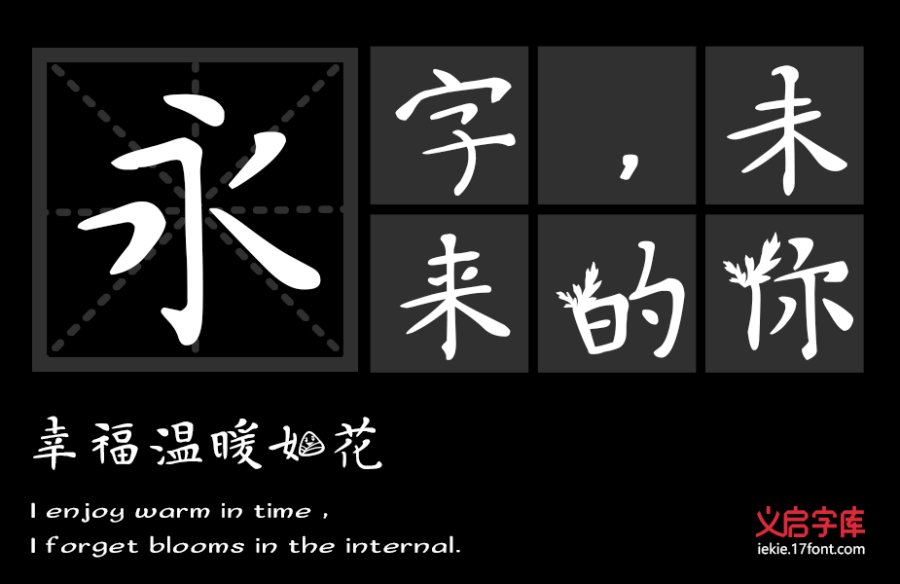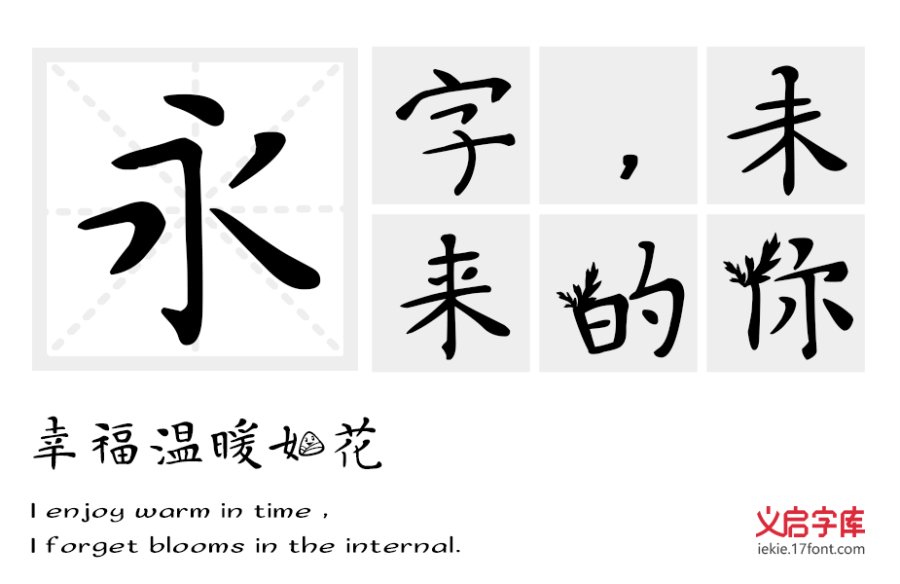
义启端午体,这款字体设计的灵感来源于端午节,是义启字库出品的节日系列字体中的其中一款节日应景字体。
端午节,又称端阳节、龙舟节等,是我国重要的传统节日。
端午节源自天象崇拜,由上古时代龙图腾祭祀演变而来。端午节有丰富的文化内涵,而且活动丰富多采,如:会挂艾叶、饮雄黄酒、赛龙舟、吃粽子等。
记得每年的端午节前后,我妈妈总喜欢在门边挂艾叶,这也加深了我对端午的情感。在义启端午体中,设计师也为字体挂上艾叶。在部分笔画上,以一片艾叶表示。飘扬的艾叶,很有时节的视觉,随风飘扬,满是春的感觉。
端午节少不了粽子,尽管南咸北甜,但人们对粽子的喜爱不减。应节的义启端午体当然少不了粽子元素,设计师在设计字体时不忘民族传统,部分“口”字偏旁的字体,以“粽子”图案代替,该图案还有眼睛笑脸,十分生动有趣,给人一种温暖亲切感。另外,如果大家平时看到一些图片字体但又不知道是什么字体名称时可以通过字体识别功能来进行图片识别字体。
在南方,赛龙舟是少不了的。特别是靠近河海地区。龙作为端午节的图腾,在义启端午体中也有表现。设计师在部分笔画中增加了“龙”的形象,非常威猛且神采奕奕。龙在中国比喻美好的事物,同时也是民族的象征。
义启端午体,带我们一起了解历史,了解传统文化。让我们知道,我们年轻的一代在在文化传承中,任重而道远。